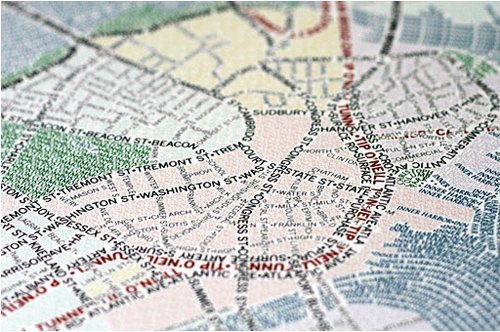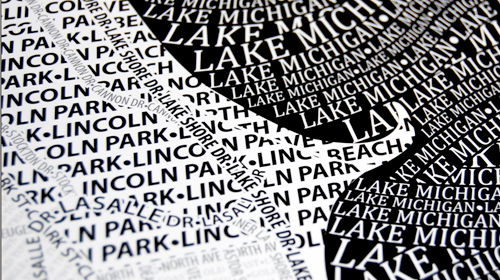
Unos Tipos Duros, fanáticos de la tipografía
Un grupo de fanáticos de la tipografía componen Unos Tipos Duros, el único colectivo tipográfico en España que se dedica a difundir las buenas prácticas en esta disciplina. Su fetichismo llega a tal punto que, cuando visitan una ciudad nueva, se dedican a recorrerla en busca de los parajes donde vivieron los grandes mitos de la tipografía. “Tienes que empaparte de eso si quieres establecer una relación de complicidad con ella”, explican.
Cuando ves una tipografía, ¿qué ves? ¿un texto? ¿un elenco de opciones en tu procesador de texto o algo más? Cuando José Ramón Penela contempla una tipografía se le abre un mundo. “Veo una preciosa historia, moda, música, expresiones de su tiempo… Tienes que empaparte de eso si quieres establecer una relación de complicidad con la tipografía. Si no, serás un usuario de ella y nada más”.
Penela es cofundador de Unos Tipos Duros, el único colectivo tipográfico de España. Defiende que, para trabajar con ella, hace falta conocerla a fondo. Para guiarle en su cometido de difundir este arte, él y sus compañeros han creado a un ilustrado filosofó tipográfico llamado Maximilian Gromenaguer. “La tipografía alimenta el espíritu, pero no el estómago”, es una de sus grandes máximas.
El proyecto nació en 2000. Poco a poco se fueron uniendo otros fanáticos de esta disciplina como Pep Patau y, posteriormente, Dimas Garcia y Marc Salinas. Cada uno cuenta con sus propios trabajos y negocios para ganarse la vida. Pero la tipografía proporciona esa fuente de alimentación espiritual que tanto persigue el ser humano. “Es algo más que poner capas encima de capas. Tiene una sintaxis, una forma de expresarse. Tiene un bagaje cultural enorme. Es un pequeño artefacto cultural a fin de cuentas”, comenta.
Tras la era de la deconstrucción, que pegó fuerte en los años 80 y 90, hay una vuelta al pragmatismo con el uso de la tipografía, según Penela. “Con esto no quiero decir que seamos más conservadores que antes. Simplemente los diseñadores se dan cuenta de la importancia de escoger la tipografía más apta para el uso que le quieras dar: ¿Quieres que te lean o estás haciendo una tipografía puntual para hacer un guiño? La gente se ha dado cuenta de que, si usa bien la tipografía, sube su nivel de expresión y aumenta su nivel global como comunicador”.
¿Las empresas son conscientes de la importancia de una buena tipografía?
Pocas, demasiado pocas. Se encuentran multitud de ejemplos de trabajos mal planteados y mal finalizados. La educación en diseño en este país sigue siendo deficiente. Muchas veces donde hay una buena tipografía también hay un buen cliente detrás. Mira el ejemplo del Naranjito del mundial del 82. Fue un mal diseño y un buen diseño a la vez, si lo comparas, por ejemplo, con Cobi. Fue una ruptura brutal. Pero detrás de Cobi no está sólo Mariscal. Está también un buen cliente.
Cuando hacemos conferencias me harto de poner ejemplos horrorosos. Sin ir más lejos, la portada de la última novela de Perez Reverte, E L A S E D I O. Ocupa toda la página. Los espacios entre las letras son kilométricos. Deja de ser una palabra. Eso era una E, una L, una A… El ritmo estaba completamente roto, abierto. Eso no era una palabra. Allí hay una ausencia evidente de conocimientos tipográficos.
Pero habrá muchos diseñadores que dirán: Me paso por el forro las reglas…
Sí, yo estoy de acuerdo. No solo puedes hacer palabras. Eric Gill decía “las letras son cosas, no imágenes de cosas”. Puedo sacarle mil matices expresivos a la tipografía. No es solamente para que te lean. Yo no estoy diciendo que hagamos textos como en el siglo 18, pero, en fin, que no dificulte la lectura si eso es lo que persigues. Que quiera hacerte un guiño. Saber lo que haces. La puedo romper, rasgar, difuminar, ser ambiguo.
Entonces los verdaderos pioneros, ¿son los que utilizan y reinterpretan las reglas establecidas o los que rompen con el pasado? ¿En qué quedamos?
Simplemente los que eligen el medio adecuado. Que tu arco de trabajo sea suficientemente amplio para saber cuándo hacer algo serio. La tipografía de edición es aquella para ser leída. Tipografía expresiva para jugar con la multitud de recursos que nos ofrece. Si tú hablas en inglés, intenta hablar en inglés; si hablas en castellano, pues en castellano. Una revista de tendencias no te va a hablar como el New Yorker.
¿Cómo ha sido el traslado de la tipografía del mundo del papel al mundo online?
Evidentemente el campo se abrió. Antes era un coto cerrado. Era un lugar al que pocos llegaban y muy especializado. Abrimos otras barreras y otras nuevas vías de comunicación hasta donde podía estirar lo que antes era una pieza de plomo y no podía hacer nada con él, salvo fundirlo. Ahora se puede y entonces mola. Todo el tema de la deconstrucción vino por la posibilidad de hacer cosas que antes no se podían hacer. Y tipos que tuvieron, se encararon en fotocomposición y pasaron a digital con mejor o peor fortuna. Se crearon unas nuevas reglas de juego. Tienes que saber cómo funciona la pantalla para saber qué tipografía puedes utilizar. Me vienen a la cabeza los títulos de crédito de Mar Adentro. Era un tipo moderno, pero ¡cómo se perdía! Solo se leía “ar aentro”. Como estaban contrastados contra un fondo con un mar, los perfiles finos se fundían. Los títulos de crédito de Ally Mcbeal, en cambio, son un buen ejemplo de un trabajo bien hecho. Tiene un contraste evidente entre blanco y negro.
¿Qué piensas sobre la utilización de tipografía de las grandes empresas españolas? ¿Que opinión te merecen las del IBEX 35, por ejemplo? ¿Qué te transmiten?